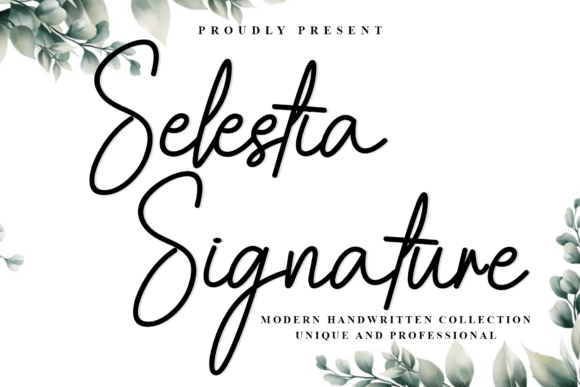
Selestia Signature
適切なデザイン要素を見つけるのは難しい場合がありますが、Selestia Signatureは作品を即座に引き立てる優れたコレクションを提供します。
POD(オンデマンド印刷)製品、結婚式の招待状、またはソーシャルメディアのグラフィックを作成している場合でも、Selestia Signatureは理想的です。